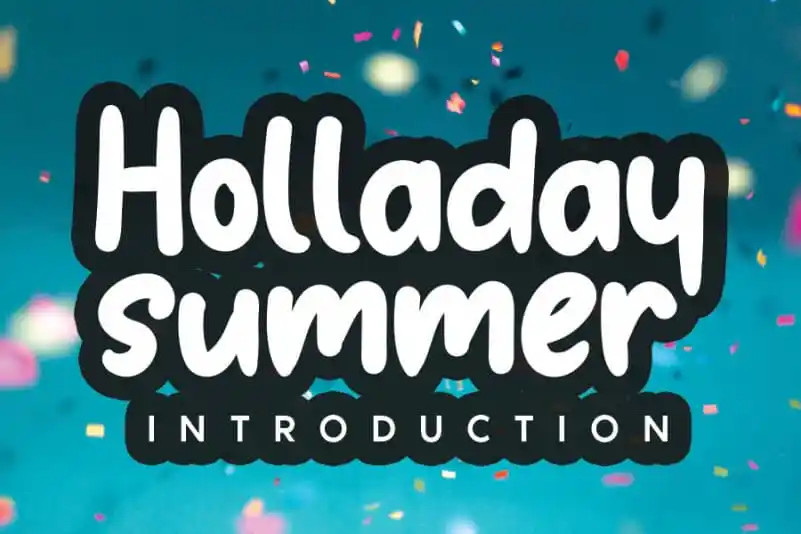
Holladay Display Font – Download Grátis
A Holladay Display Font é uma fonte de display elaborada cuidadosamente para se tornar um verdadeiro favorito. Seu charme casual a faz parecer muito acessível, fácil de ler e, acima de tudo, extremamente versátil. Esta fonte brilha em qualquer contexto, seja ela usada em fundos agitados ou como uma grande headline sozinha. Com Holladay na sua composição, você está garantido de criar trabalhos que ressoam com eficácia e elegância em todos os ambientes. Seja para um site de negócios moderno ou para uma publicidade memorável em outdoors, a Holladay Display Font é uma escolha confiável.